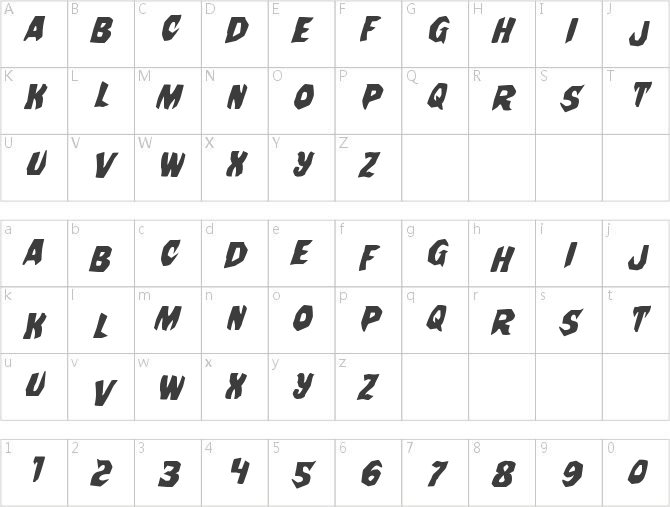
Nightchilde Staggered Italic
Nightchilde Staggered Italic介紹
Nightchilde Staggered Italic字體字庫是一款讓人賞心悅目、百看不厭的英文字體,適合各類廣告和產品包裝設計應用,字體大小0.05MB,格式為ttf字體,上傳用戶是后天的昨天,作者/版權方為未知